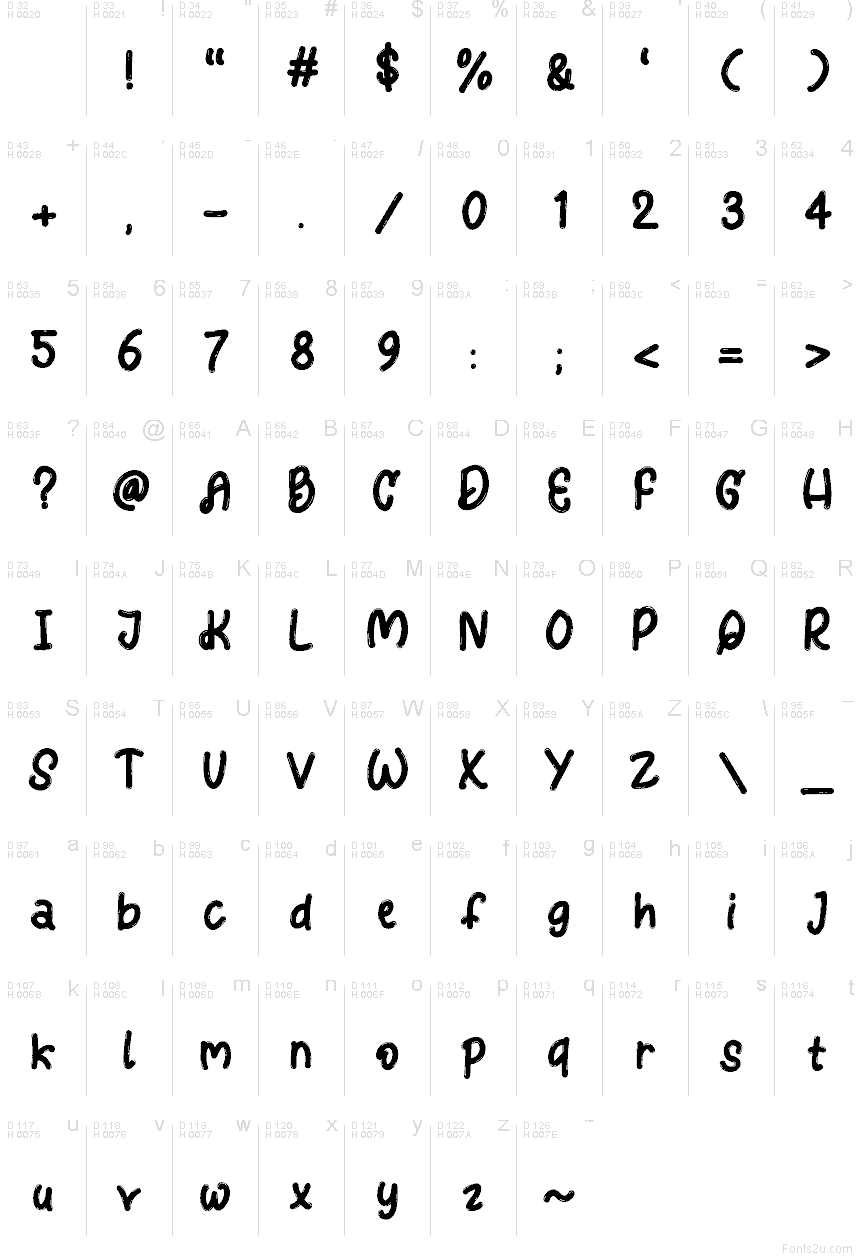
Bigspace Rocket
Bigspace Rocket de Yumnacreative est une police de caractères typée cartoon, gratuite et idéale pour l'affichage, avec des lettres arrondies dessinées à la main, des contours irréguliers et un rythme dynamique et pétillant. Les formes semblent esquissées plutôt que construites, avec des courbes douces, un espacement compact et un tracé vivant qui donne à cette famille un caractère de bande dessinée ou d'enseigne.
Bigspace Rocket fonctionne parfaitement pour le packaging jeunesse, les titres de BD, les citations sur affiches, les logos de jeux vidéo, les stickers et l'identité visuelle décontractée, car ses formes dégagent naturellement une énergie créative. Cette police gratuite apporte cette touche authentique aux logos, aux visuels pour réseaux sociaux, à la signalétique de boutique et aux flyers événementiels lorsque vous souhaitez un rendu informel et sur-mesure.